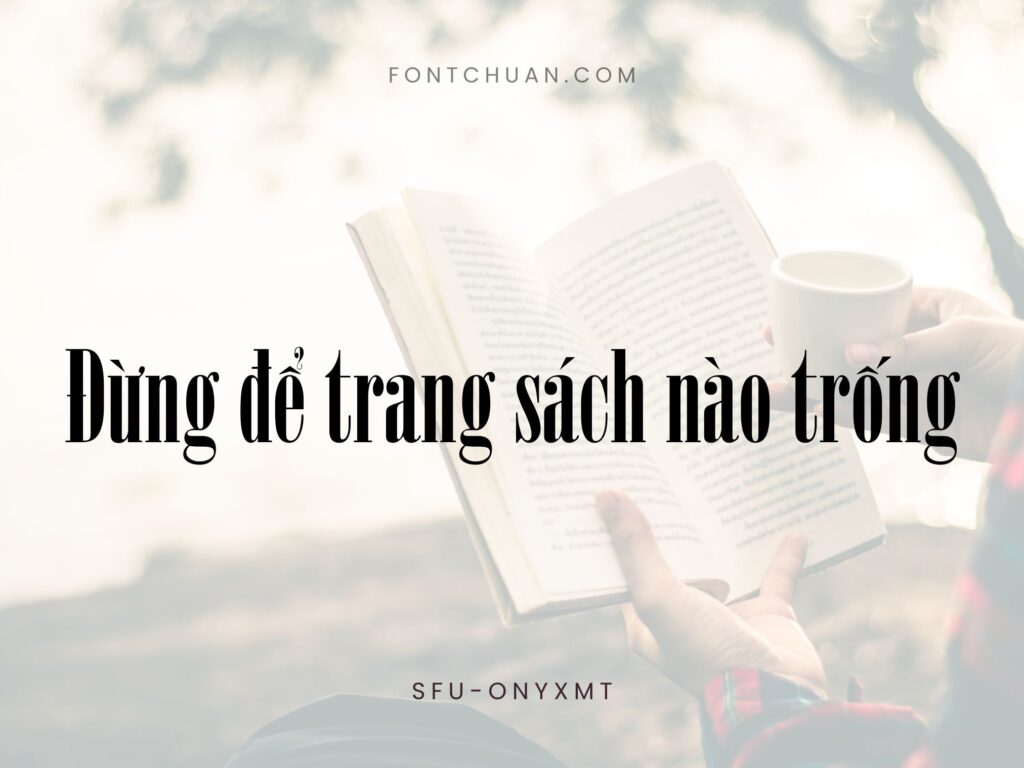
Onyx MT là một kiểu chữ serif được thiết kế với phong cách thanh mảnh và cao, tạo nên sự độc đáo và thu hút trong các thiết kế tiêu đề và quảng cáo. Font này được sưu tầm và đăng bởi thành viên của Font Chuẩn. Với thiết kế đặc trưng, Onyx MT không chỉ phù hợp làm Font logo cho các thương hiệu muốn thể hiện sự sang trọng và tinh tế, mà còn được ứng dụng rộng rãi như một Font chữ quảng cáo trong các poster, banner hay ấn phẩm truyền thông.
Về mặt thiết kế, Onyx MT có các đường nét mảnh mai và cao, tạo cảm giác tinh tế và hiện đại. Font này hỗ trợ nhiều ngôn ngữ và bao gồm các ký tự đặc biệt, giúp người dùng dễ dàng tùy chỉnh theo nhu cầu. Onyx MT thường được sử dụng trong các thiết kế tiêu đề, poster, bao bì sản phẩm và các dự án cần sự nổi bật. Các ngành nghề như quảng cáo, thiết kế đồ họa và truyền thông có thể tận dụng kiểu chữ này để tạo dấu ấn đặc biệt trong truyền thông.